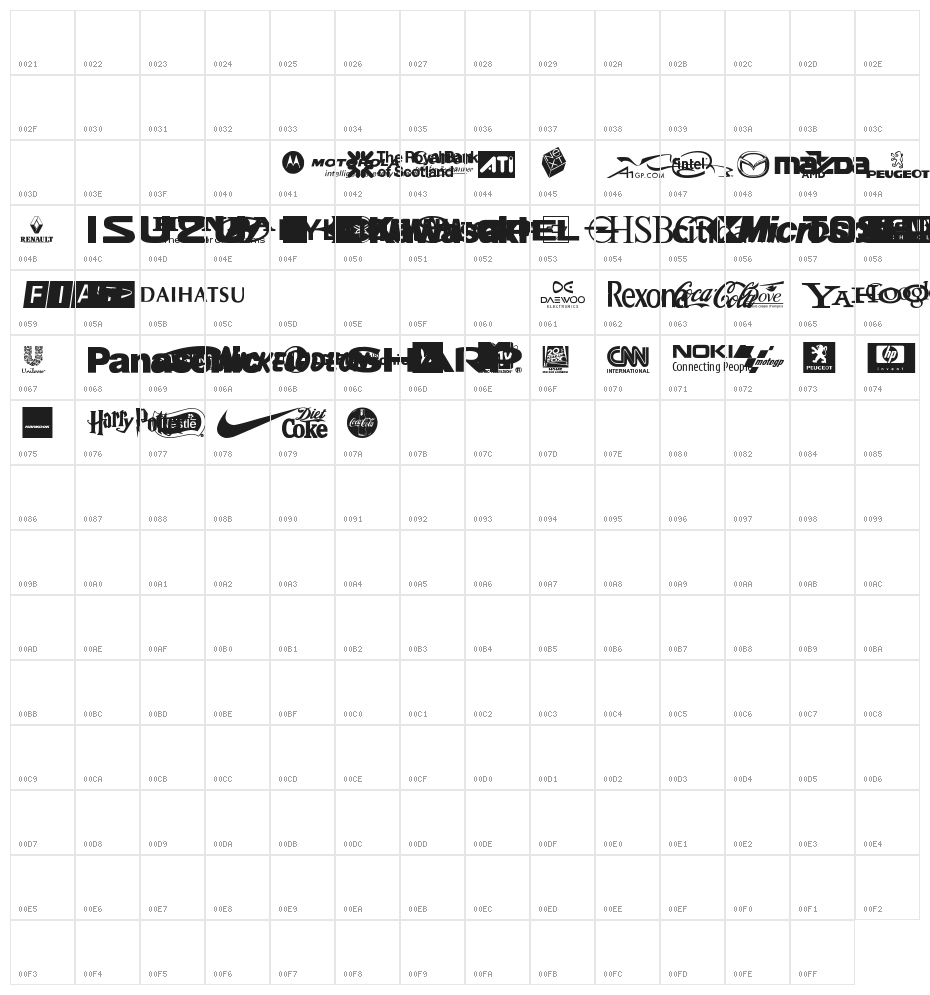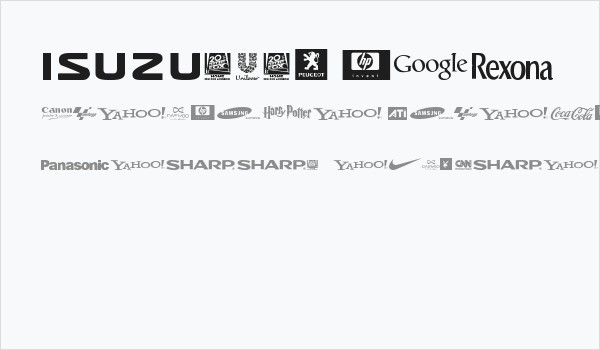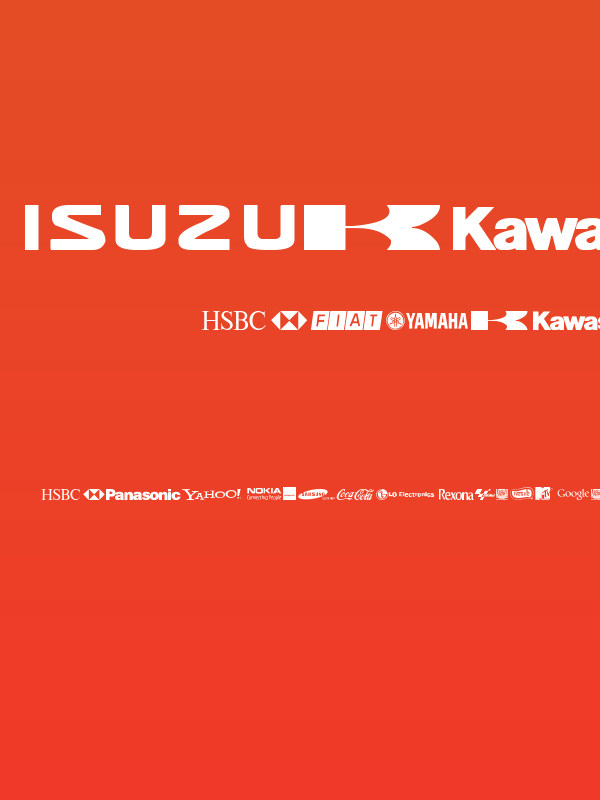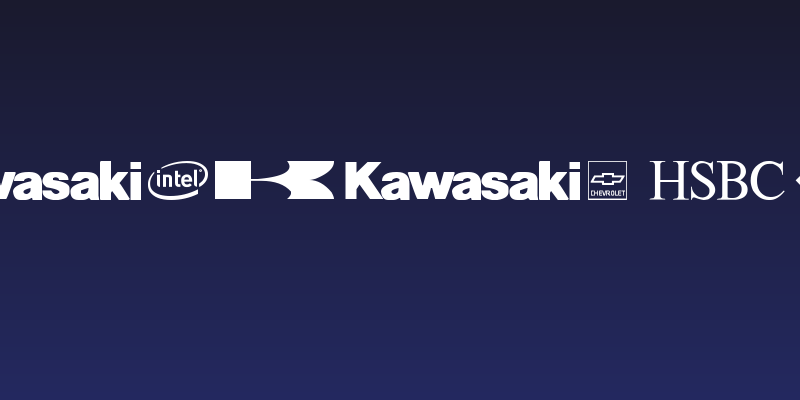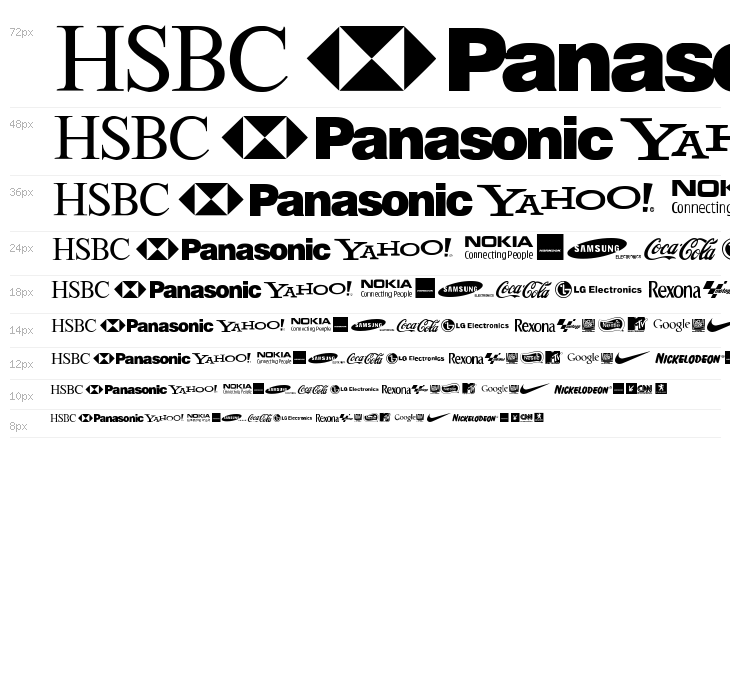
Logos tfb Font
| Stile generale | Decorative, Modern, Classic, Script, depending on the logo |
| Caso d'uso | Logos, Branding, Advertising |
| Progetti proposti | Branding mockups, advertising concepts, logo studies, educational materials on branding, and design inspiration boards. |